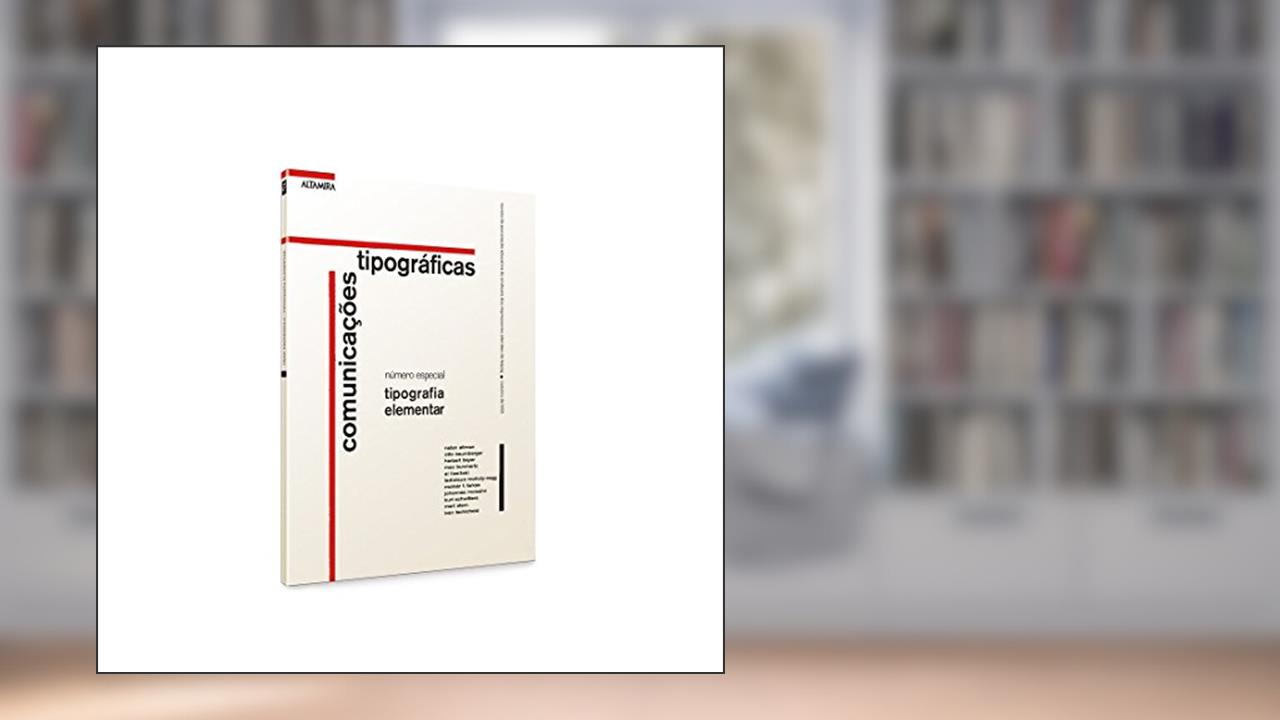
Tipografia Elementar: Comunicações Tipográficas não é apenas uma coletânea de letras; é uma verdadeira obra-prima de Jan Tschichold que revela a profundidade e a relevância da tipografia na comunicação moderna. Com uma abordagem direta e científica, este texto traz à tona a mágica que as letras exercem sobre a percepção humana, um tema que ressoa poderosamente em um mundo saturado de imagens e textos.
Tschichold, um nome reverenciado na história do design gráfico, provoca você a enxergar além da superfície da tipografia. 🖋 Ele não se limita a discutir como letras se organizam nas páginas; ele te instiga a compreender como elas moldam ideias, emoções e até mesmo comportamentos. A sua visão inovadora nessa obra é como uma lâmpada acesa em uma sala escura. Ao longo de suas 60 páginas, você é guiado por conceitos fundamentais que vão desde a simplicidade até a complexidade da comunicação através de letras.
A obra salta aos olhos em meio a um cenário onde a comunicação visual é frequentemente negligenciada. Não é apenas um convite à reflexão, é um grito por atenção. O que você verá em tipografia não é só o que os olhos enxergam, mas o que a mente absorve. O design da letra pode mudar o tom de uma mensagem, transformar intenções e, por fim, influenciar a ação. É uma dança sutil entre o significado e a forma, que Tschichold destaca com maestria.
Os leitores que mergulham nesse trabalho vão se deparar com opiniões polarizadas. Alguns exaltam a profundidade da análise de Tschichold, enquanto outros contestam a sua abordagem técnica, considerando-a hermética demais para o público leigo. Entretanto, quem aprecia a riqueza do design e suas intrincadas relações com a comunicação, encontra aqui uma fonte inesgotável de inspiração. As críticas, embora divisivas, apenas ressaltam a força da obra, mostrando como a tipografia é um campo fértil para debates e reflexões.
E não é só isso. Ao perpassar os ensinamentos de Tschichold, você também descobre como essa obra influenciou gerações de designers e apaixonados pela comunicação visual, moldando o trabalho de ícones que trouxeram novas dimensões ao design gráfico. Cada letra, cada espaço, cada curva é um conceito que se desdobra em novas possibilidades. Uma tipografia bem feita não é apenas estética, ela é uma declaração que converge arte e funcionalidade.
Em um mundo onde a informação é frequentemente diluída e perdida no caos, Tipografia Elementar surge como um farol, lembrando a todos nós a importância dos detalhes e da intenção no que comunicamos. Tschichold te convida a não apenas ler, mas sentir e entender a tipografia como uma parte essencial da nossa existência cotidiana. Sinta essa conexão e permita que a tipografia transforme sua perspectiva. Essa é uma viagem que vale cada letra, cada espaço e cada ponto. 🌟
📖 Tipografia elementar: comunicações tipográficas
✍ by Jan Tschichold